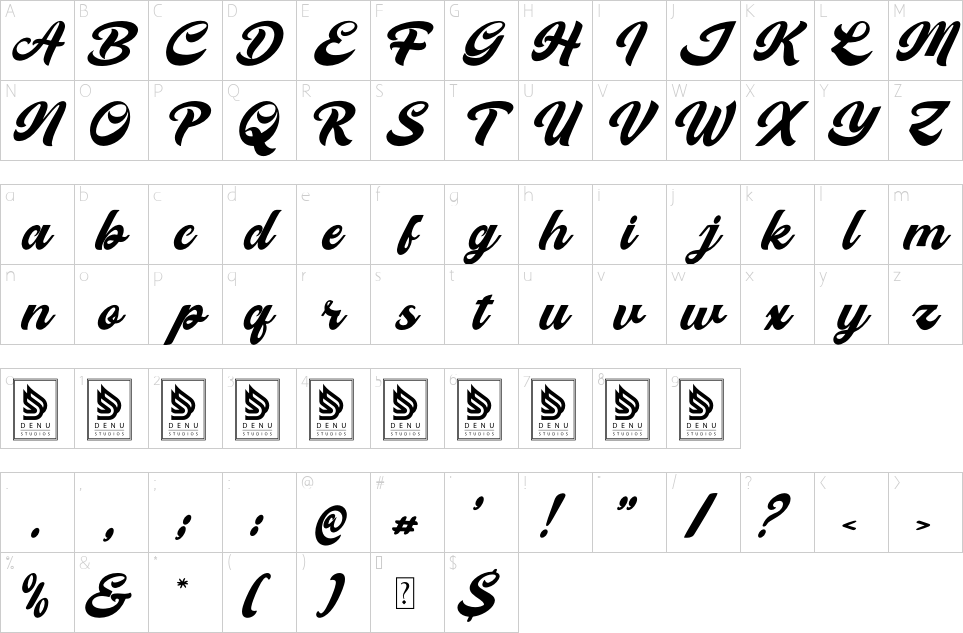
Melcostra é uma fonte de texto cuidadosamente elaborada pela Gracetypestudio, disponível de forma gratuita tanto para sistemas Windows quanto Mac. Ela combina um aspecto moderno com sutilezas elegantes, perfeita para uso em sites, redes sociais e em projetos de design gráfico. Com uma aparência sóbria e detalhada, a fonte oferece uma maneira estilosa de escrever e formatar texto, tornando-a uma opção versátil para designers e criativos que valorizam uma fonte grata. Suas características foram criadas pensando em oferecer um equilíbrio entre estética e funcionalidade, tornando-a uma opção ideal para qualquer projeto que deseje um toque diferenciado. Com a fonte Melcostra, a experiência de design gráfico ganha um toque de elegância e sofisticação.